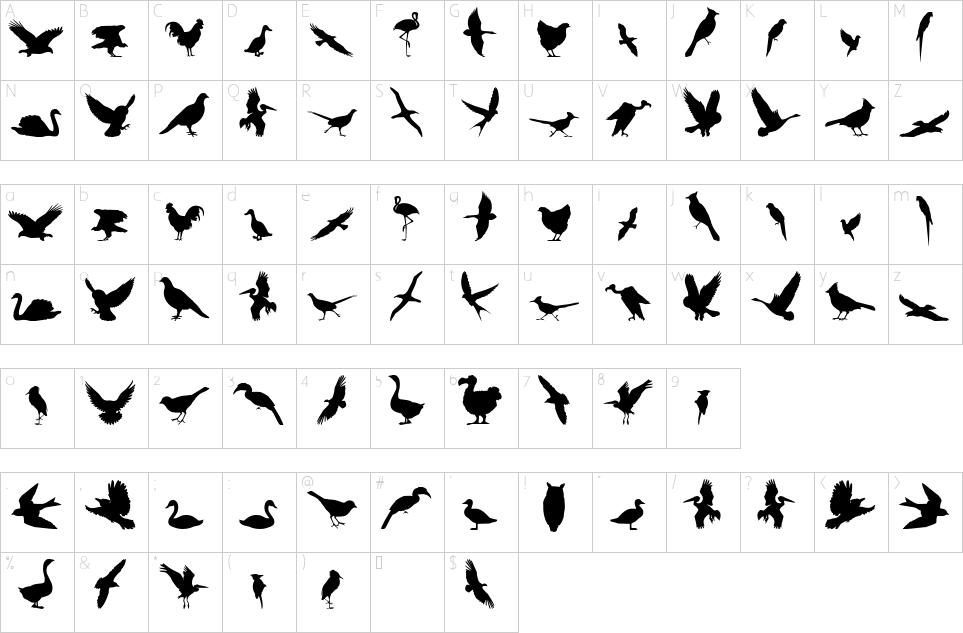
A fonte ‘Birds Of A Feather’ é um recurso gráfico gratuito disponível para Windows e Mac. Introduzida pela Iconian Fonts, essa fonte tem sido baixada mais de 106.926 vezes. Suas linhas leves e elegantes tornam-a uma opção perfeita para designers que desejam dar um toque atraente a seus projetos digitais. Com um design minimalista, a fonte Birds Of A Feather combina facilmente com diversos estilos de design, desde logos e e-mail personalizados até artigos de blog e cartões de visita. Seja você um amante de pássaros ou simplesmente fascinado por design de fontes, essa fonte é uma excelente escolha para quem busca uma opção gratuita e de qualidade.